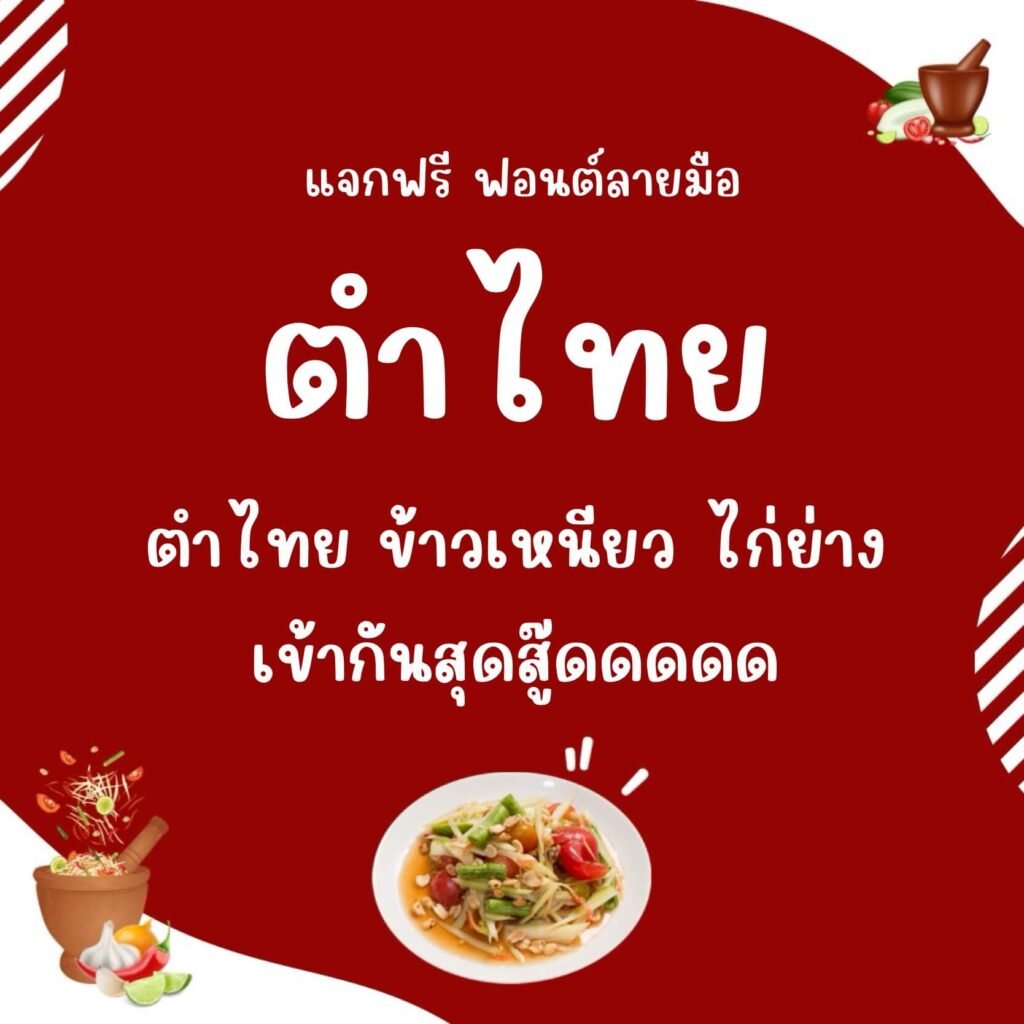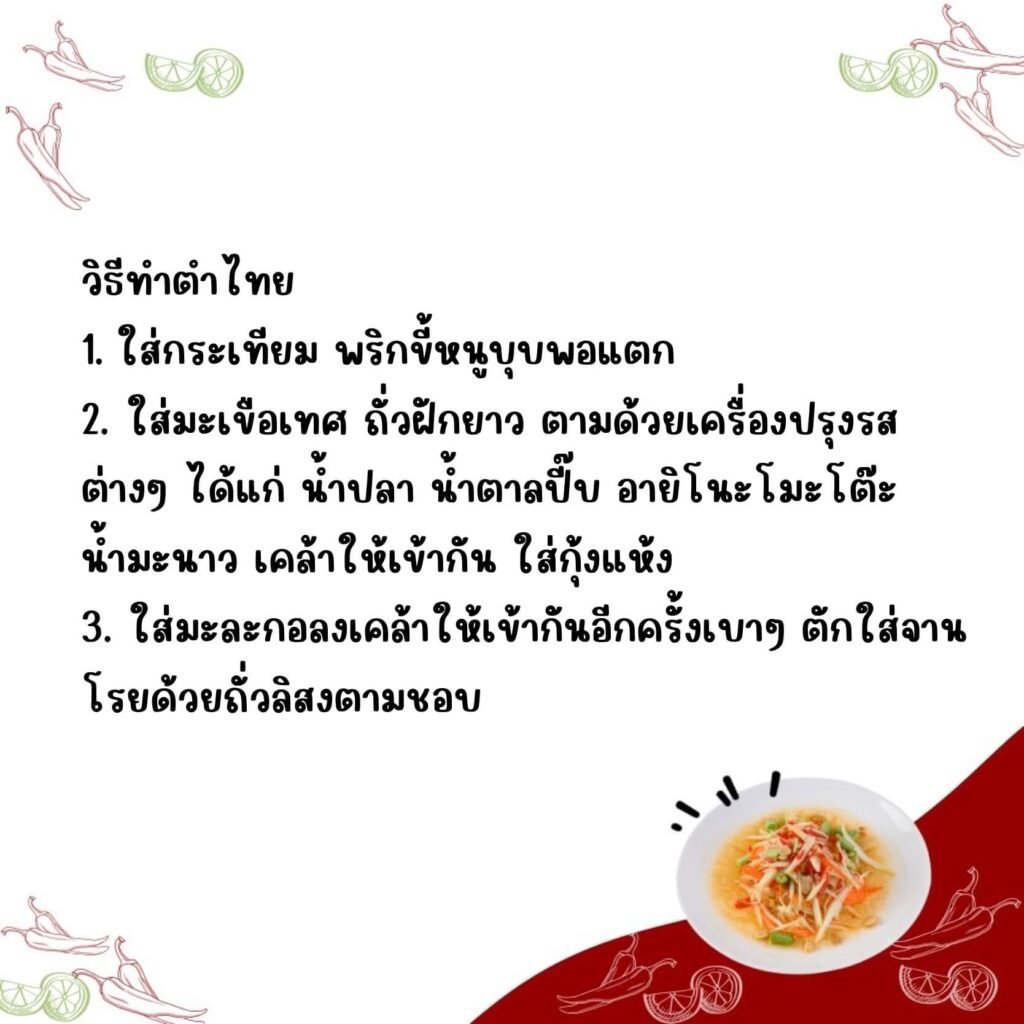
ตำไทย (Tumthai)
แจกฟรี !! ฟอนต์ลายมือ ตำไทย (Tumthai) สำหรับใช้งานส่วนตัว 1 น้ำหนัก (บาง) สำหรับจดโน้ต สรุปงานส่งอาจารย์และงานที่ไม่ก่อเกิดรายได้เท่านั้น